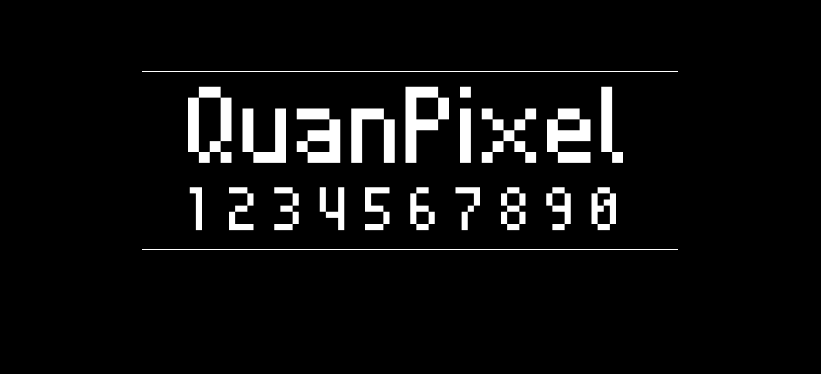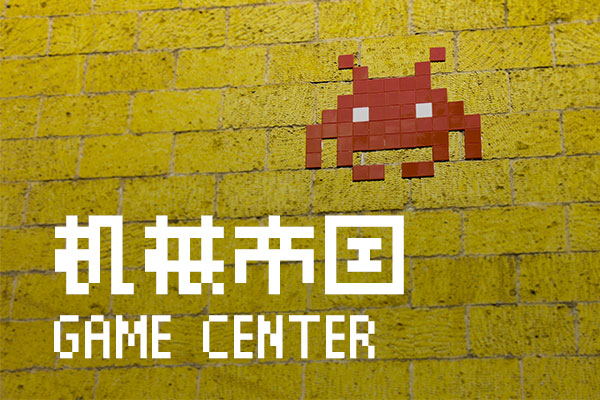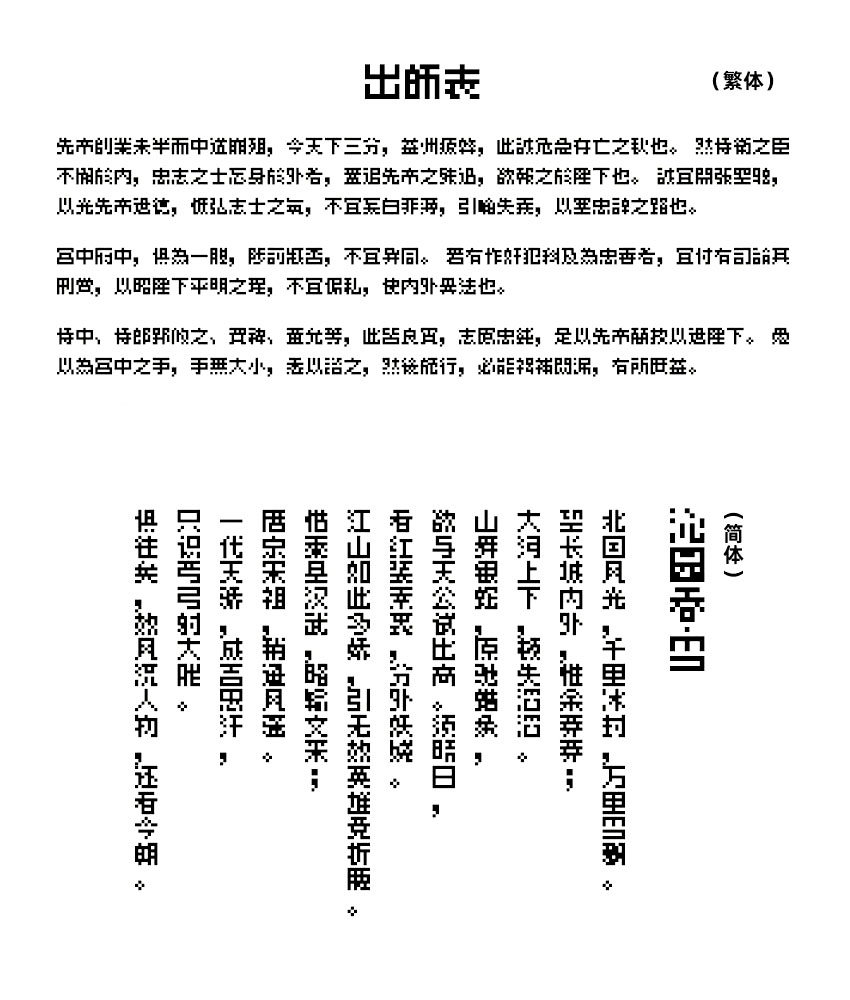
全小素
全小素(QuanPixel 8px 8px)是一个8×8的像素字体,包含了很多中文、日文、韩文字符,其字符来源于多款免费字体:Galmuri、Chill 点阵体;目前已覆盖简体中文GB2312标准的6763字,繁体BIG5标准5401字,对中文的支持还是很不错的。
像素风格的字体并不少见,但是8×8大小的中文字符就很少了,主要原因在于字符较小,有些字笔画就会糊在一起,所以在笔画的精简上就成为了该字体的重点,既要缩小尺寸,又要能辨认出表达的字形,还是有一些难度的。